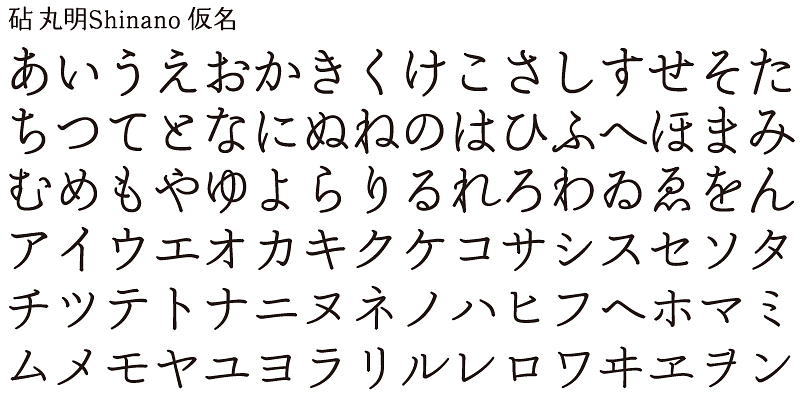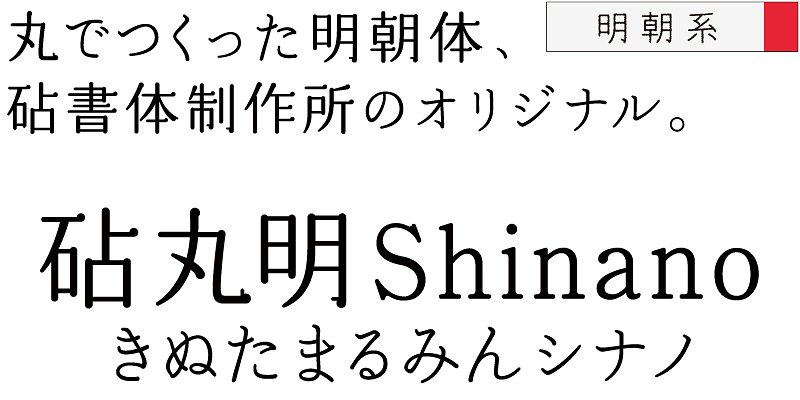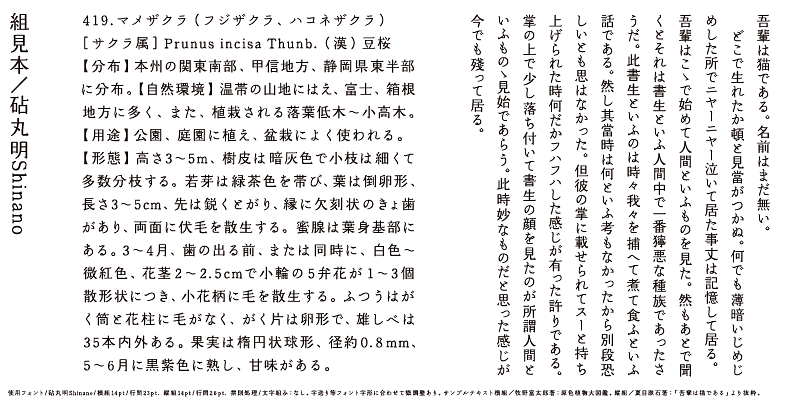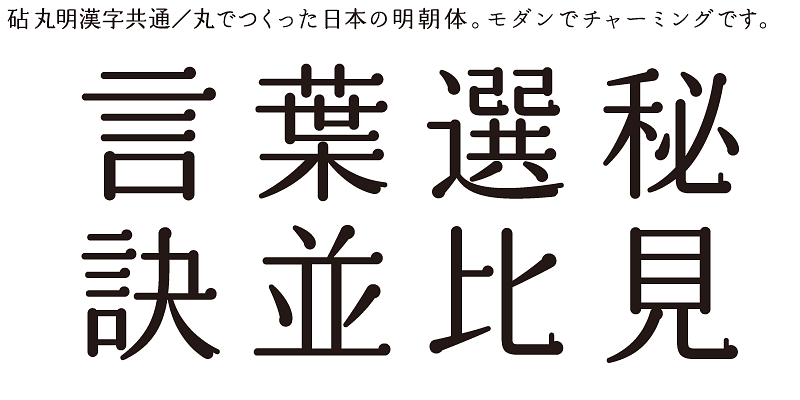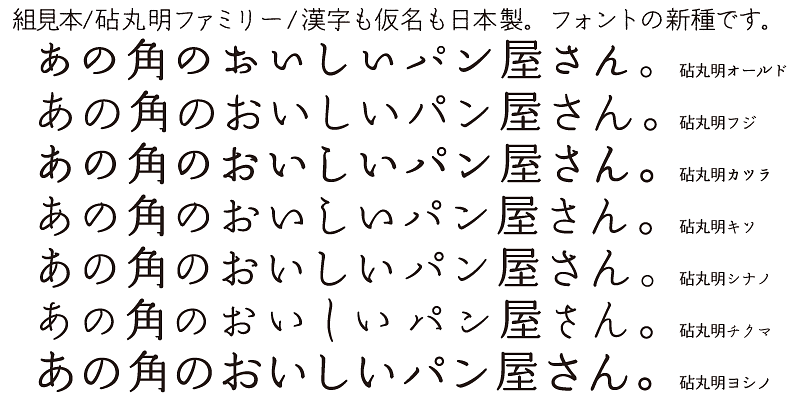
Das Kana-Zeichen-Design der MaruminShinano basiert auf einer Pinselschrift aus dem Zeitalter der Bleisatzschriften, fügt aber einen Hauch von Eleganz in der Bewegung der Pinselstriche sowie eine glänzend polierte Textur hinzu. Diese Schrift eignet sich für eine breite Palette von Zwecken.
Alle Marumin-Varianten haben die gleichen ideografischen (Kanji-)Zeichen. Das Design der Kanji-Zeichen der Marumin basiert auf dem Stil der japanischen Mincho-Schrift, hat aber Strichelemente mit abgerundeten Merkmalen. Die Enden der horizontalen und vertikalen Striche, die Punkte sowie die Formen der Tome- und Harai-Striche sind alle abgerundet. Marumin führt eine neue Kategorie „Rounded Minchotai“ mit insgesamt sieben Kana-Varianten ein.
Ein Merkmal der japanischen Sprache sind ihre Kana-Silbenzeichen. Kana-Zeichen wurden in Japan erfunden, um japanische Laute darzustellen und aus China importierte Texte ins Japanische zu übersetzen. Kana-Zeichen werden benötigt, um japanische Wörter und Ausdrücke aus Kanji (chinesischen ideografischen Zeichen) zu erstellen. Auch wenn es Zweideutigkeiten gibt, zeigen diese Wörter und Ausdrücke die Wärme und Sanftheit des Lebens der Menschen, die in dem kleinen und dicht besiedelten Japan leben.
Kinuta Font Factory ist davon überzeugt, dass Kana-Zeichen der Ursprung auf Japanisch geschriebener Wörter sind, und wir glauben, dass die Optimierung von Kana-Zeichen japanische Texte attraktiver macht. Im Durchschnitt bestehen 60 % der japanischen Texte aus Kana-Zeichen – ändert sich die Form dieser Zeichen, verändert das auch das visuelle Erscheinungsbild des Textes. Die Möglichkeiten des typografischen Ausdrucks mit einfachen, dynamischen und kurvenförmigen Kana-Zeichen sind enorm und die Üppigkeit japanischer Texte hängt von Kana-Zeichen ab. Aus diesem Grund bietet Kinuta Font Factory viele Variationen von Kana-Schriftarten an.